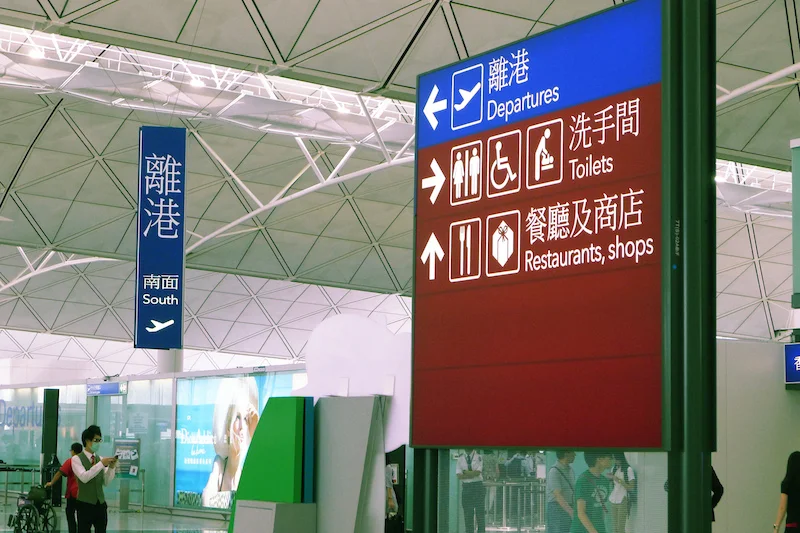
把新細明體用在機場指標上,不是這個社會最麻煩的問題,卻反映某種根深柢固的「細節盲」症候群──對環境中嚴肅的設計問題缺乏思考,認為指標這種東西,只要看得懂就可以,不必要求太多。這是一種意識形態,認為該把時間精力花在刀口上,而不是枝微末節的小事(例如字體)。這就是為什麼我們的國門,桃園機場第一航廈的指標全都用了新細明體。
但就像前一篇說過的,在某些地方,例如公路、機場,字體還真不是枝微末節的小事。這個資訊承載者的表現,影響讀者的體驗感受,甚至我們的人身安全。
機場是「第一印象」,各方面設計都會影響旅客對當地的觀感;偌大而龐雜的空間設施,也需要有良好的導引,才不會讓旅客迷路。甚至,發生緊急狀況時,指標要能適時發揮作用,引導安全的逃生路線,保護旅客的生命安全。
以上這些重大任務:形象、導引、公共安全,桃園機場第一航廈交給了新細明體,就是你我電腦裡都有的系統字型。這字體真的可以勝任這些任務嗎?
不過,指標的呈現不只關乎字體,還有背板材質、發光方式等面向,在評價指標看板時都要一併考慮。若有問題,也是這些因素的綜合。
他山之石,不一定可以攻錯
話說從頭,這樣的規劃甚至還是向香港機場借鏡的。原本,香港機場指標設計之所以採用新細明體,可能是為了讓旅客看得更清楚,因為字體細,所以筆畫不會糊在一起。
攝於香港赤鱲角機場,字體是新細明體
以下是我們在台大醫院看到的狀況。台大醫院指標燈箱也是同樣材質、同樣發光方式,但卻使用了過粗的字體,使得筆畫都糊在一起了。
從遠方看,這些字就像一塊塊發光體,絲毫沒有發揮導航的功能。在長廊上,面對看不清字的指標,根本不知道怎麼找到自己要去的處室。反觀台北捷運、高鐵的指標系統,都是背景全黑,只有文字發光的設計,這種設計若採用較粗的黑體,也比較不會有模糊問題。
台灣高鐵的指標,只有文字會發光
受既定材質與發光影響,桃園機場第一航廈的指標使用新細明體,看來是很理智的選擇,可以讓字看來更清楚。但這樣的結果讓我們滿意嗎?
可視性:萬眾矚目或隱而未顯
這個指標設計解決了一個問題,卻衍生出更多問題。這個案例,便是「可視性」(visibility)不夠的問題。可視性,指的是從一段距離之外可以輕易發現指標存在的特性,同時可以閱讀、辨認;如果要旅客、使用者跑到指標正下方才能看清楚指示方向,便失去了指標的意義。
一般用在內文的細明體最大的特色是什麼呢?就是細(好像廢話)。例如你現在所看到的這段文字,是不是跟前後的黑體明暗度差很多呢?就是因為它的細,所以不管在螢幕或印刷內文,都不至於糊在一起。但也是因為「細」,導致這個字體在版面上並不那麼「亮」。傳統中文印刷術語裡,明體又叫「白體」,也是這個原因。
將這議題搬到指標上,就能說明「可視性」問題是怎麼回事。新細明體用在指標是為了防止模糊,解決的是「易辨性」(legibility)問題。但新細明體的「可視性」不理想:比起黑體,細明體相對暗淡,並不引人注目。連注目都無法獲得,更不用談能否辨認了。
而且,這還只解決了發光設計所引發的易辨性問題。為了指標系統的一致性考量,桃園機場的許多標示都採用了新細明體,包含不會發光的電梯前告示、垃圾桶標示等等。比起能發光的告示來說,這些不會發光的新細明體又更難讓人從遠處注意到了。
問題還不只在高調或低調。可憐的新細明體,放大後不一定更加引人注目,但卻很可能會被嫌「好醜」。
看起來醜,不是新細明體的錯
新細明體最大的美感問題,可能是因為長時間擔任系統字型導致的審美疲乏,因此無法體會它的「美感」。它是典型的,小字時很素雅、大字時很乾癟的字體。因為它本來就是針對「內文」而設計的字體,字裡面的空間配置也是針對小空間設計的。
它的功能性很強,在解析度不高的電腦螢幕上,這字體縮小後照樣讓人讀得懂、用得上。用在報告內文,則可確保輸出效果不會因為軟硬體的差異而受影響;沒有突出個性的特點,也不會讓讀者分心,可以專注在內容上,這就是為什麼有些學院規定寫論文要用新細明體。
雖然小塚明朝、儷宋評價都很好,但是放到這麼大,看起來也跟新細明體差不多
但是新細明體放大之後白色的範圍過多,黑色的線條太少。用在版面標題──視覺的注目焦點上,好象營養不良的肉,毀了整道主菜的口感。其實,把一個很細的、針對內文設計的明體放大到指標大小,評價大概都不會高到什麼地步。用於內文的明體,與用於標題的明體,本來就是不一樣的東西。不信的話,我們把設計業界評價優良的小塚明朝EL與儷細宋放到很大,跟新細明體比較起來,還真是半斤八兩。
橫筆加粗的明體比較適合指標
好看的指標可以讓建築物更有質感,也會增進各地旅客的第一印象。但可惜的是,放到這麼大的新細明體,恐怕很難讓人有什麼好印象。不過,要特別說明的是,明體不是不能用在指標,只是若要發揮良好的性能,就必須經過調整。上圖中間橫筆適當加粗,比起左右,是比較理想的標識明體設計。
有了易辨性,卻犧牲旅客體驗
如同前述,這種看板材質與發光方式下,新細明體的確解決了糊在一起的問題,但是,放大到指標大小的新細明體,並不容易引人注目,也不美觀。
或許有人會說「功能比較重要」,但是功能與美感並非對立的概念,它們都是使用者體驗的一環。現代設計的理念,固然注重能否解決問題,但卻也從未排除「美感」此一向度。美感也是功能的一部份,讓使用器物的人更愉悅,更能沉浸其中。它跟現在講究的形象、品牌,也是關聯在一起的。畢竟,對於初來乍到的旅客來說,機場的設計就是第一印象。更何況,新細明體作為指標,也無法滿足「可視性」的功能需求。
為了兼顧功能與美感,設計團隊往往要反覆實驗,才能得到令人滿意的結果。香港機場、桃園機場的指標設計就停在(半調子的)功能性面向,而沒有更進一步思考怎麼平衡功能與美感。國際機場指標設計的優良範例,如法國巴黎戴高樂機場、東京成田機場的指標,就針對發光方式、背板材質、字體設計與排版上,有更用心的研究與經營。
國際上眾多機場、車站指明使用的 Frutiger 字型,本來就是專為法國巴黎戴高樂機場設計的。
目前的國際設計潮流是也將通用設計(universal design)概念引入指標設計,也有專門為此目的設計的「UD字體(UD是通用設計的簡稱)」。或許可以考慮引進UD字體,但是桃園機場指標的問題不僅出在字體而已,它需要針對發光方式、背板材質、字體設計,與資訊流呈現方式大改造。作為建物內導航與形象的代表物,指標系統是值得投資的「使用者體驗」設計,而不是枝微末節的門面妝點工程而已。